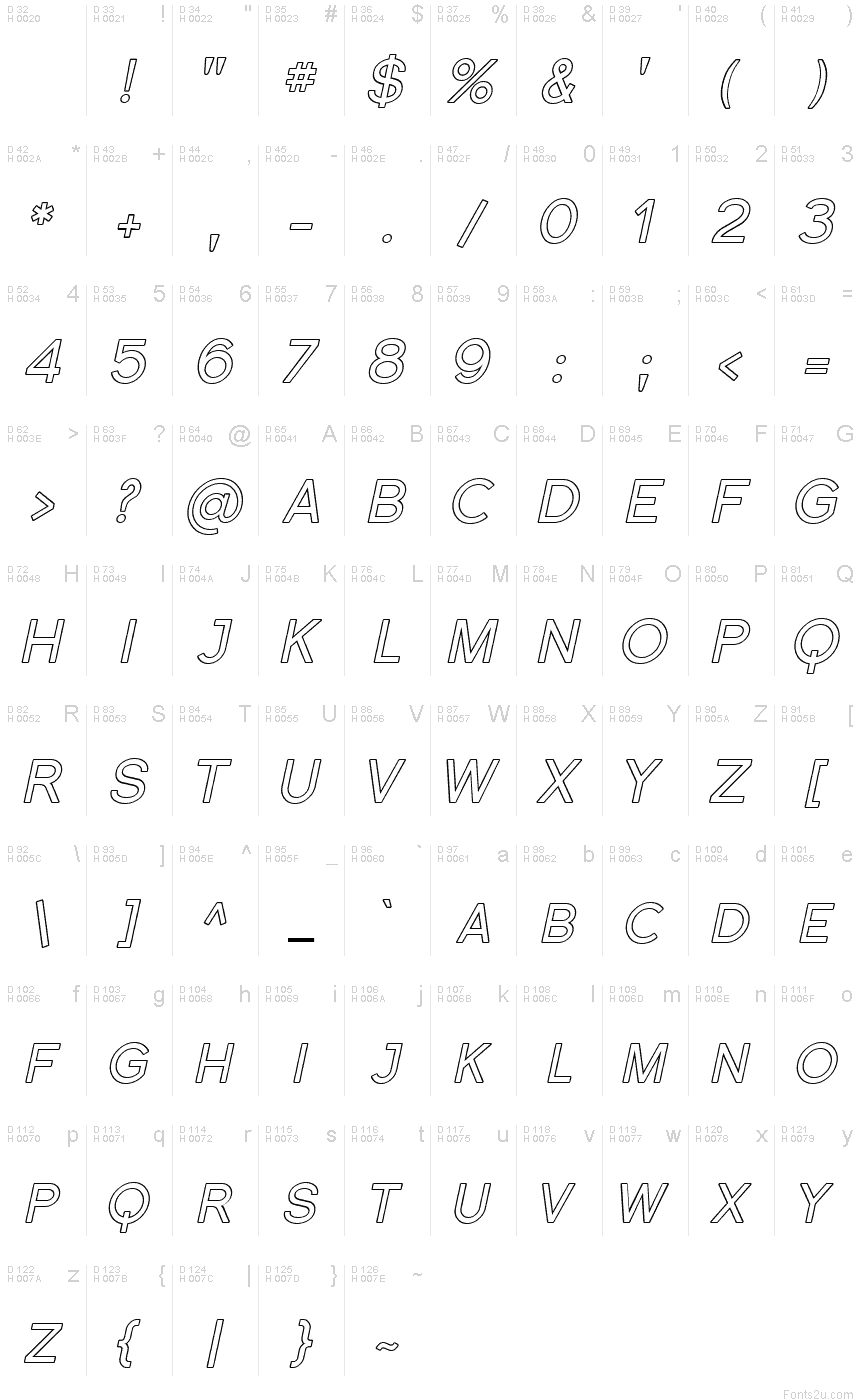
Florencesans SC Outline Italic
Florencesans SC Outline Italic autorstwa Dereka Vogelpohla to darmowy, bezszeryfowy krój konturowy o czystej, zwiewnej strukturze, która sprawia wrażenie jednocześnie wyrazistej i lekkiej. Litery pochylają się do przodu z płynną energią kursywy, a pojedyncze kreski tworzą wyraźny, techniczny kontur, który niemal świeci na jasnym lub ciemnym tle. Jako część rodziny Florencesans SC Outline, zapewnia spójną geometrię i mocny charakter małych kapitalików, który doskonale sprawdza się w ciasnych układach.
Korzystając z Florencesans SC Outline Italic, możesz tworzyć efektowne plakaty, okładki albumów, logotypy w stylu neonowym, branding wydarzeń technologicznych, opakowania oraz odważne grafiki do mediów społecznościowych, które wyglądają jak nakreślone światłem. Ten darmowy font błyszczy w dużych rozmiarach, pozwalając pustym formom „oddychać” i współgrać z kolorem, fakturą lub fotografią w tle. Połącz go z prostym, neutralnym krojem bezszeryfowym w tekście głównym i pozwól, by Florencesans SC Outline Italic przejął najbardziej przykuwające uwagę momenty.